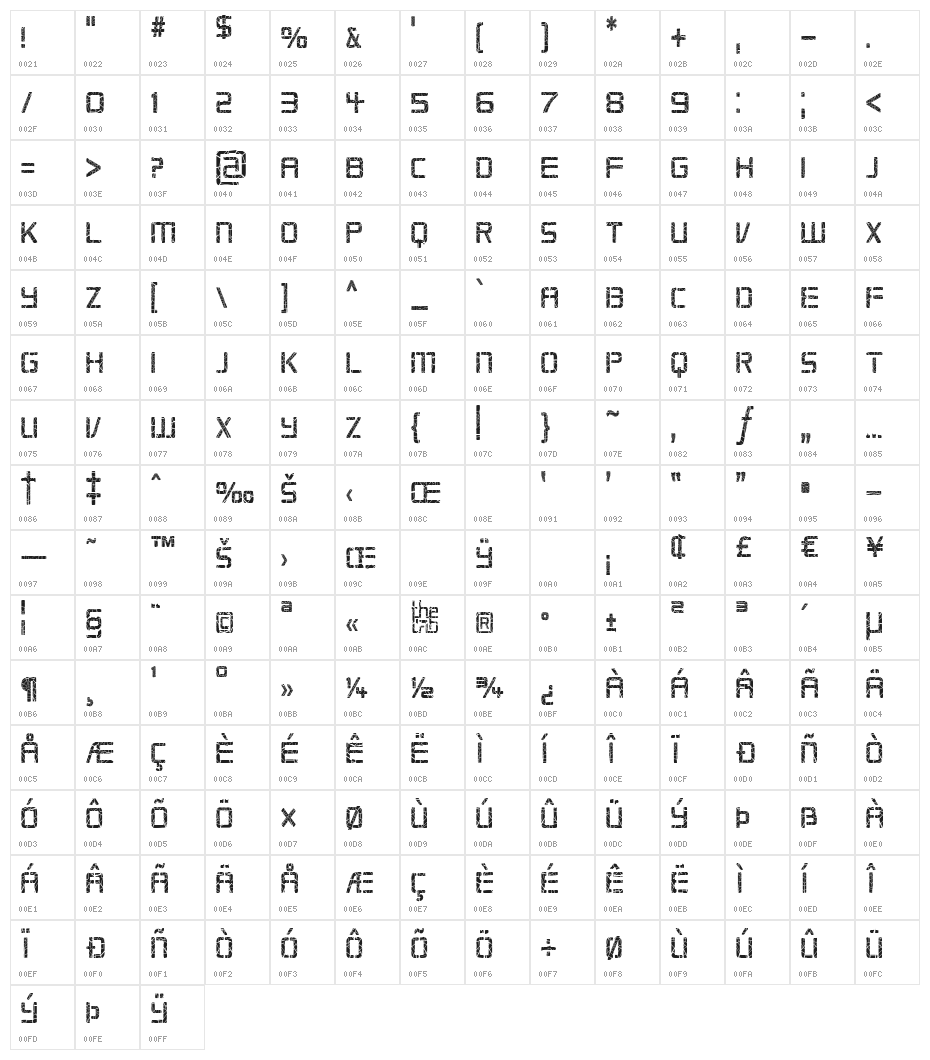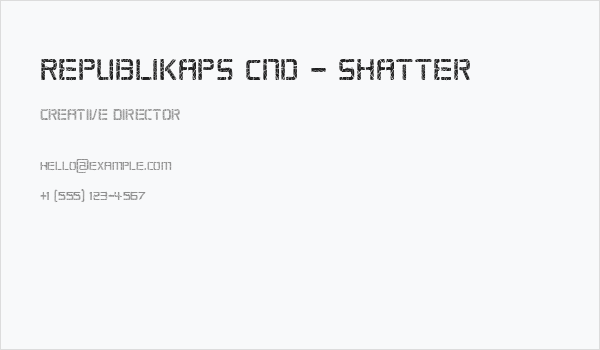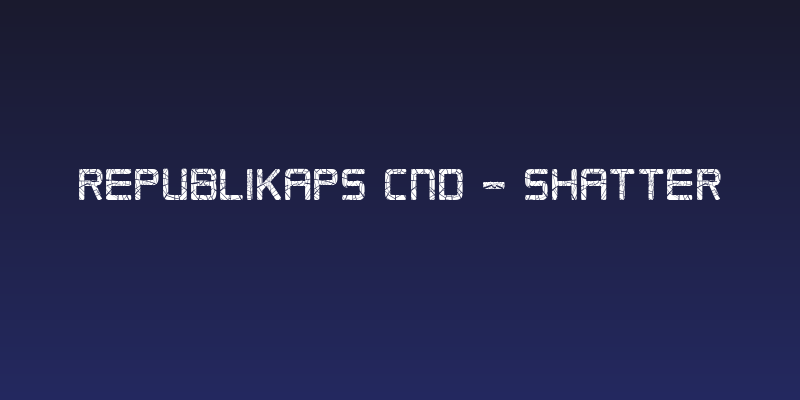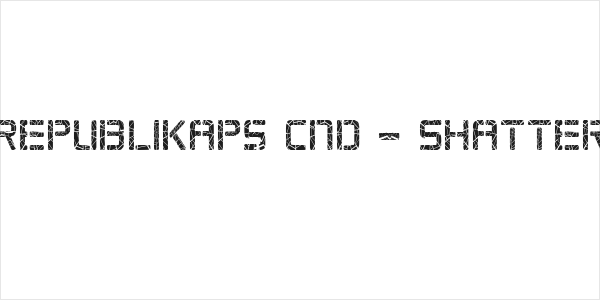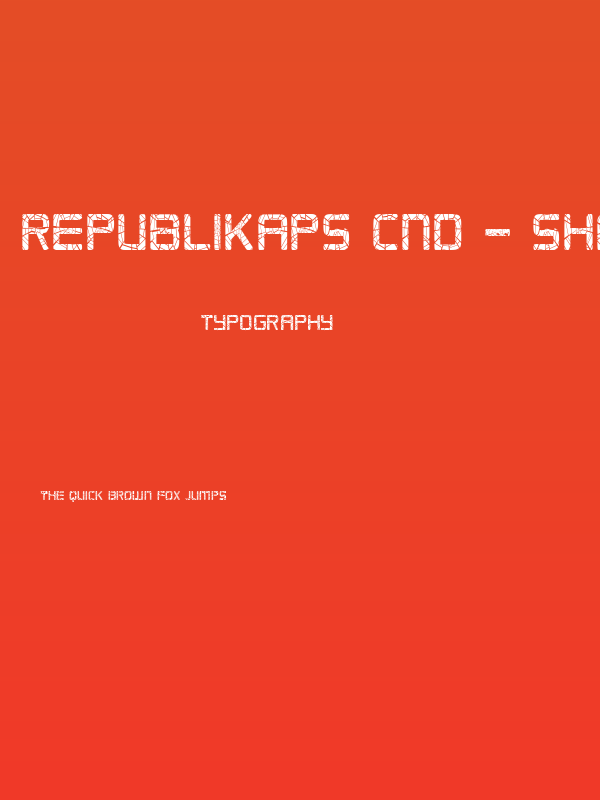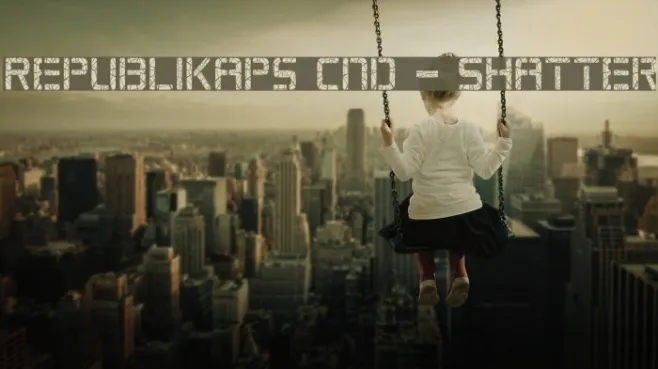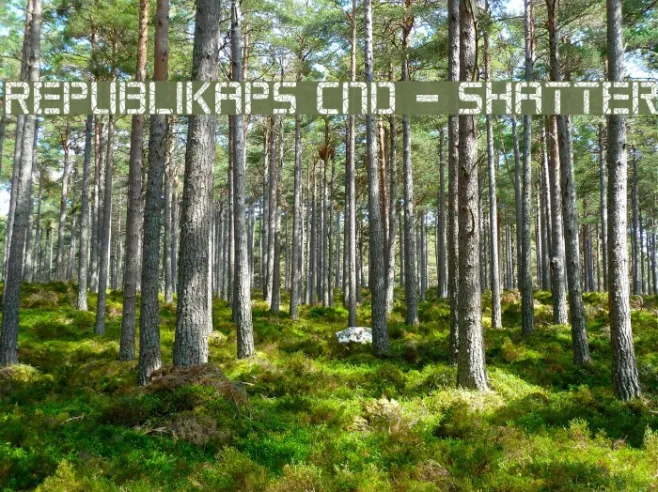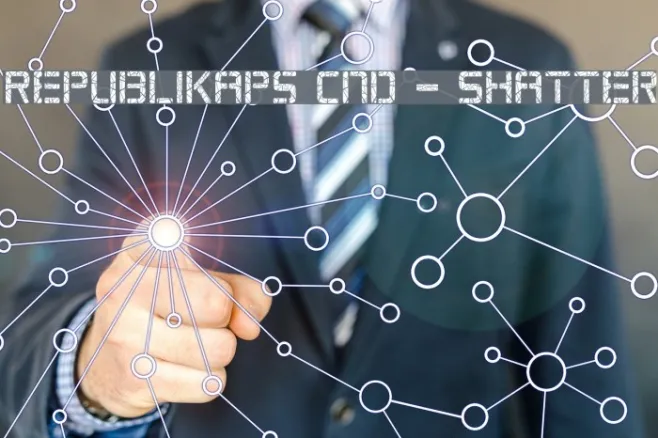
Republikaps Cnd - Shatter Font
✎ Distorted Eroded
| Progetti proposti | Ideal for projects requiring a bold statement, such as posters, album covers, branding for edgy products, or digital art. |